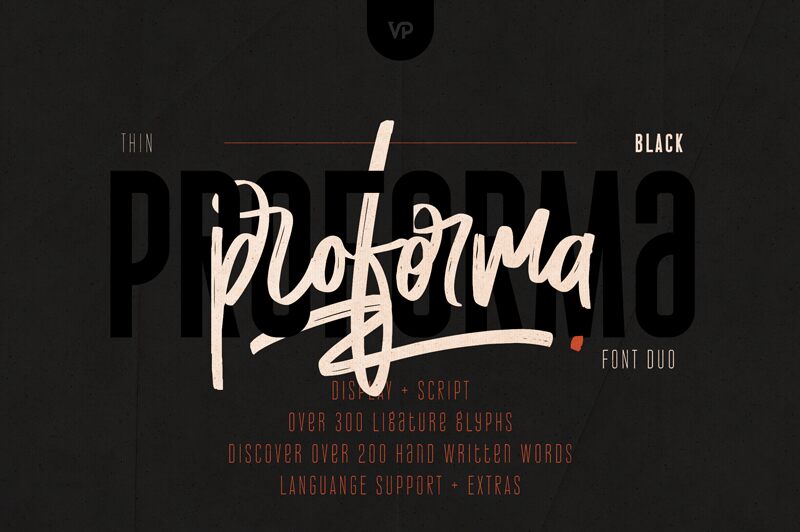
Proforma Free Demo
Proforma é uma fonte display retro gratuita com letras altas e estreitas e cantos suavemente arredondados. A sua construção de traço único confere às formas um ritmo elegante e aerodinâmico, enquanto os remates arredondados mantêm uma sensação mais suave do que uma típica sans-serif condensada.
Proforma funciona muito bem em títulos de cartazes, logótipos, capas de álbuns, sinalética de lojas e citações editoriais, uma vez que a sua postura vertical transporta uma forte presença gráfica sem necessidade de decoração extra. Proforma também se adapta a embalagens, gráficos para eventos e branding de inspiração vintage quando precisa de uma fonte display estreita que pareça limpa, estilizada e ligeiramente nostálgica.